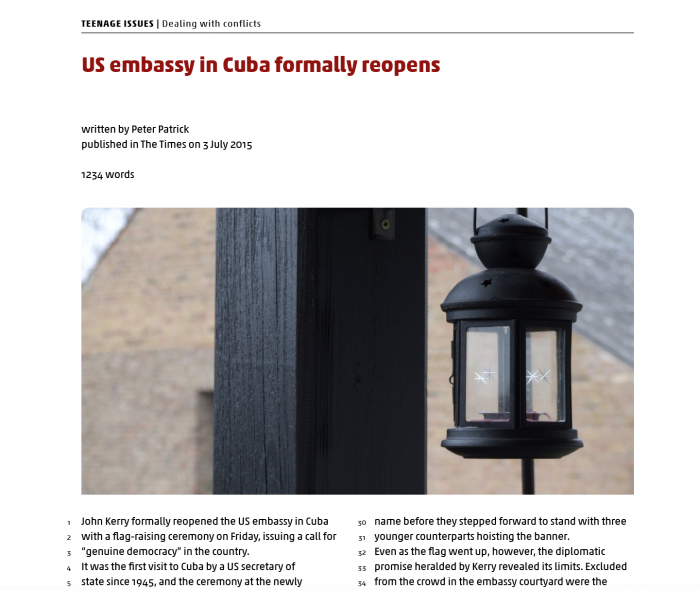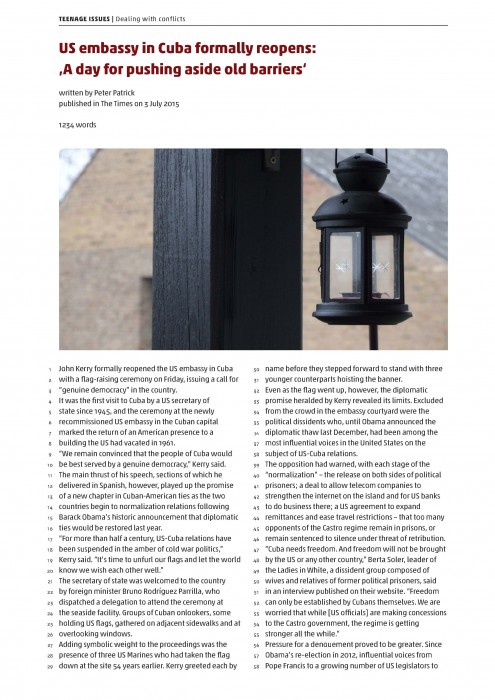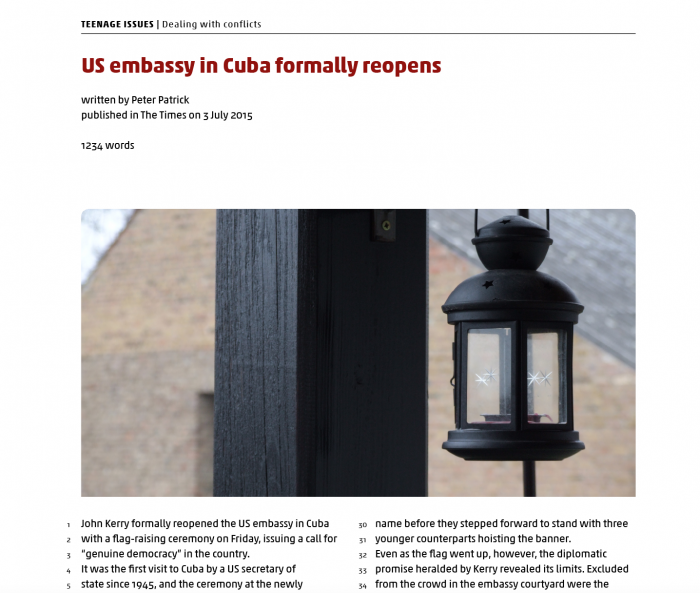
Gestaltung von ein- und zweizeiligen Überschriften
Ich habe eine Dokumentvorlage, wo sich zukünftig ein- und zweizeilige Überschriften befinden werden (siehe Datei "Dokumentvorlage.pdf").
Jetzt frage ich mich, wie ich vorgehe, wenn ich anstatt einer zweizeiligen Überschrift nur eine habe.
1.) Lasse ich die zweite Überschriftszeile einfach leer (Variante A)?
2.) Lasse ich die erste Überschriftszeile leer (Variante B)? oder
3.) Rücke ich den darauffolgenden Text (Autor, Quelle, Wortanzahl) einfach nach oben? (Variante C)?
Oder gäbe es eine Variante D?
Auf den Folgeseiten fängt der Fließtext allerdings immer auf der Höhe von der ersten Überschriftszeile an.
Ich wäre sehr dankbar für Eure fachkundigen Vorschläge. Vom Gefühl her würde ich Variante A bevorzugen.
Warum darf das Bild mit dem darunterstehenden Text nicht nach oben rutschen, wenn der Kopf eine Zeile kürzer ist? Dann wären die Räume im Kopf immer gleich und alle Abstände auf der Seite auch.
Es ist natürlich Ansichtssache. Aber ich würde das Bild auch immer an der gleichen Stelle setzen. Das Bild  „springt“ sonst beim Durchblättern. Wenn die Möglichkeit besteht, sollte man die Bilder nach einem festgelegten Raster setzen.
Variante 3 wäre für mich akzeptabel.
Bei Variante 1 stört mich der variierende Abstand zwischen Überschrift und Autor.
Bei Variante 2 würde die Satzspiegeloberkante variieren.
Das „Springen“  der Bilder ensteht, wenn dem Layout kein Gestaltungsraster zugrunde liegt.
Dass die Möglichkeit, mit einem Gestaltugsraster zu arbeiten, nicht immer gegeben ist, ist mir bewusst.
Im konkreten Fall bietet sich das aber geradezu an. So sehe ich das jedenfalls.
Wenn es aber möglich ist, setze ich die Bilder ebenso auf einen festgelegten Raster, wie die Typografie.
Das Festlegen des Gestaltungsrasters ist für mich eigentlich die wichtigste Arbeit bei der Buchgestaltung. Hier wird auch festgelegt ob die Gestaltung „lebhaft“ oder „ruhig“ wirken soll.
Mir ist die Ursache der Wirkung schon klar. Aber was wäre gegen das Springen der Bilder zu sagen? Müssen alle Bilder auch das gleiche Format und die Texte die gleiche Länge haben? Warum sollen sie nicht springen? Worin besteht der Wert? Ich habe schon öfter Bildbände gemacht, aber mir war es nie wichtig, welche Effekte sich beim Blättern ergeben. D.h. Blättern in dem Sinne, daß man den Buchblock mit einer Hand festhält und nach vorn oder hinten die Seiten durchrasseln läßt wie im Daumenkino. Das erschien mir nie als wichtiger Aspekt des Buchentwurfs. Sobald man langsam blättert und Bilder und Texte anschaut, wird diese Wirkung doch marginal, oder nicht?
Mir ist die Ursache der Wirkung schon klar. Aber was wäre gegen das Springen der Bilder zu sagen?
Formal nichts. Aber das heißt im Umkehrschluss ja nicht, dass die Gestaltung mit festem Raster irgendwie nicht legitim wäre. Ich halte beide hier gerade diskutierten Varianten für völlig akzeptabel und würde die Wahl von der konkreten Anwendung abhängig machen.
Wenn auf vielen Seiten der Aufbau so ist, dass auf die Überschrift immer ein Bild und dann der Lesetext folgt, würde ich Variante A anwenden. Wenn das Dokument aber mehr reine Textseiten enthält, würde ich Variante C wählen.
Müssen alle Bilder auch das gleiche Format und die Texte die gleiche Länge haben?
Über den Sinn des Gestaltungsrasters wurden mehrere Bücher von sehr kompetenten Fachleuten geschrieben, darum verstehe ich deine Frage nicht.
Aber bitte: Einen Gestaltungsraster zu verwenden, heißt nicht, dass alle Bilder gleich groß und alle Texte gleich lang sein müssen. Ganz im Gegenteil: Vielfalt wird in ein (begründbares) System gebracht.
Es geht aus meinem Beitrag ja hervor, sofern die Möglichkeit besteht, würde ich einen Gestaltungsraster auch für Bilder verwenden.
Für mich ist eben nicht die Einzelseite des Buches das Wichtigste sondern das Zusammenspielen aller Seiten zu einem Buch.
Das heißt nicht, dass es dabei um Vereinheitlichung der Seiten geht. Ich verwende dann oft viele Musterseiten, mit denen dann trotz Vielfalt ein geschlossenes Gesamtbild entsteht.
Über den Sinn des Gestaltungsrasters wurden mehrere Bücher von sehr kompetenten Fachleuten geschrieben, darum verstehe ich deine Frage nicht.
Vielfalt wird in ein (begründbares) System gebracht.
Für mich ist eben nicht die Einzelseite des Buches das Wichtigste sondern das Zusammenspielen aller Seiten zu einem Buch.
Ich kann mich nicht erinnern, ob ich eines dieser Bücher mal gelesen habe. Wenn, dann ist mir nichts davon geblieben. Ich erinnere mich dunkel, daß auch gegen Rastertypografie argumentiert wurde, vielleicht erschien mir das einleuchtend. Die Begründbarkeit des Systems kann ich noch nicht erkennen. Warum ist dieser Blättereffekt so wichtig? Das Zusammenspiel der Seiten ergibt sich doch nicht allein dadurch, daß Bilder beim Durchblättern nicht springen, sondern durch Format, Papier, Bindung, Schrift, Satzspiegel und Inhalt.
ich habe mal eine Beispiel-Doppelseite mit Kommentaren aufgebaut, wie ich es machen würde.